Police de caractères vs police : quelle est la différence entre une police et une police de caractères ?
Publié: 2022-05-25Le débat "police de caractères contre police" est quelque chose que vous êtes susceptible de rencontrer si vous poursuivez une carrière dans la conception graphique ou la stratégie de marque. Pour le profane, il est facile d'utiliser les deux termes de manière interchangeable pour désigner le style ou la conception d'un ensemble particulier de caractères sur un écran.
Cependant, demandez à un designer professionnel "quelle est la différence entre une police et une police de caractères ?" et ils seront souvent en mesure de vous donner une explication complète des significations individuelles.
Les polices de caractères et les polices ont un rôle important à jouer dans le monde du design. Ce sont des termes que les entreprises doivent définir pour s'assurer qu'elles maintiennent une image de marque cohérente sur une multitude de supports et de canaux.
Aujourd'hui, nous allons examiner en détail le débat « polices de caractères contre polices » pour vous aider à mieux identifier les deux.
La différence entre la police de caractères et la police
L'argument police vs police n'est pas aussi complexe qu'il y paraît. En termes simples, une police de caractères fait référence à un ensemble de caractéristiques de conception choisies pour les lettres et autres caractères, tandis que les polices font référence à la variation de taille et de poids d'une police de caractères spécifique.
Une police fait partie d'une police de caractères. Par exemple, Times New Roman est une police de caractères, avec un ensemble complet de caractères serif parmi lesquels choisir et une philosophie de conception cohérente. Cependant, il existe différentes «polices» dans la famille Times New Roman.
La différence entre une police et une police de caractères a été établie pour la première fois à l'ère de l'imprimerie. Le mot « font » vient du français « fonte », qui signifie « couler dans du métal ».
Les imprimeurs coulent des ensembles entiers de lettres métalliques pour constituer une police. Ils auraient besoin de différentes «polices» pour les italiques, les lettres en gras et les polices de caractères de différentes tailles.
Alors que le paysage numérique des polices de caractères signifie qu'il n'est plus nécessaire de créer des blocs métalliques pour l'impression dans différentes polices, les concepteurs utilisent toujours ces termes de manière régulière.
Définir la "police" d'une police de caractères spécifique permet de s'assurer que les professionnels de la marque peuvent transmettre l'image unique d'une entreprise aussi précisément que possible.
Fait intéressant, il n'y a aucune distinction entre les polices et les polices de caractères en termes informatiques, comme si vous aviez installé la police de caractères Helvetica sur un Mac ou un ordinateur, vous pouvez la rendre entièrement dans une multitude de polices différentes, pour s'adapter à différentes échelles.
Cependant, nous utilisons toujours des polices dans les applications de traitement de texte et de publication assistée par ordinateur. Vous pouvez voir la différence entre une police de caractères et une police en ouvrant votre document Word et en cliquant sur la fenêtre qui dit quelque chose comme "Arial" ou "Calibri"
La liste des noms apparaissant lorsque vous cliquez sur cette fenêtre sont les "polices de caractères", tandis que les différents éléments entourant la fenêtre, de la taille du type, aux options gras, italique, souligné ou barré, vous donnent votre alternative polices.
Si cela semble compliqué, plongeons un peu plus profondément.
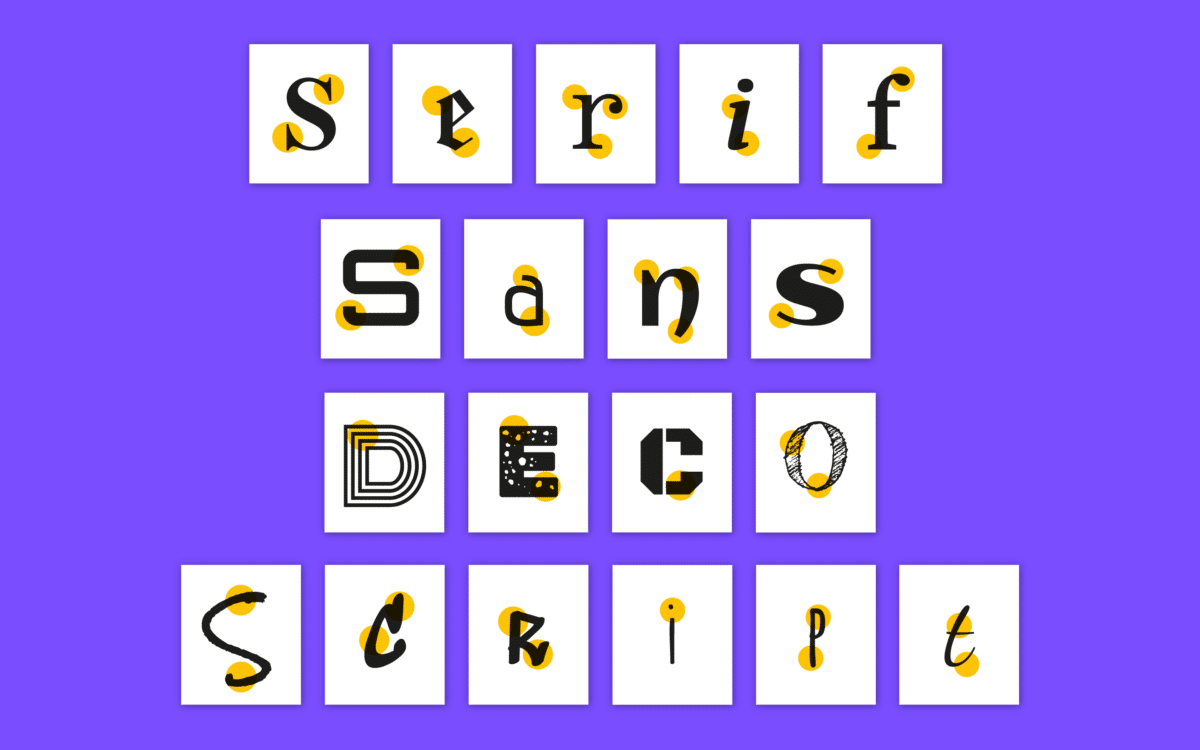
Polices de caractères et polices : qu'est-ce qu'une police de caractères ?
Une police de caractères est un ensemble spécifique de caractéristiques de conception choisies pour une série de caractères et de lettres. Par exemple, si vous regardez la police Arial, vous remarquerez une police simple sans empattement avec des courbes et des lignes soigneusement espacées.
Une police de caractères définit les éléments qui rendent un ensemble de caractères unique, des empattements spécifiques aux fioritures et à l'équilibre des lettres majuscules et minuscules.
Il existe de nombreux styles de caractères différents, tels que :
Serif
Les polices de caractères Serif sont définies par les "empattements" ou les pieds sur diverses lettres. Ce sont quelques-unes des polices de caractères les plus traditionnelles disponibles aujourd'hui, souvent associées à des concepts tels que l'héritage, l'histoire, la sophistication et la crédibilité.
Sans empattement
Une police de caractères sans empattement est une option plus moderne, amicale et conviviale destinée à rendre les entreprises et les marques plus détendues et informelles. Ces polices de caractères éliminent les pieds "empattement" des lettres et créent ainsi une image plus décontractée.
Les polices de caractères sans empattement sont souvent très faciles à lire et sont courantes dans le monde numérique.
Décoratif
Une police de caractères décorative utilise une multitude d'éléments différents, des empattements et fioritures accrocheurs aux éléments tourbillonnants pour capter l'attention de leur public.
Les polices décoratives sont généralement destinées à de plus petites quantités de texte que les alternatives sans empattement ou avec empattement, car leurs éléments compliqués peuvent les rendre un peu plus difficiles à lire.
Scénario
À ne pas confondre avec une police écrite en italique, une police de caractères de script est lorsque les lettres et les caractères sont conçus pour ressembler à une écriture manuscrite naturelle et cursive. Ces polices sont les plus courantes chez les marques qui souhaitent obtenir une touche unique, conviviale et artisanale pour leur esthétique.
Semblables à leurs homologues décoratifs, les polices de caractères script peuvent être difficiles à lire dans des tailles plus petites, ce qui signifie qu'elles sont plus couramment utilisées pour les en-têtes et les logos.
Polices et polices de caractères : qu'est-ce qu'une police ?
Donc, si une police de caractères est l'élément de conception nécessaire pour différencier les caractères de différents groupes, qu'est-ce qu'une police ? En termes simples, le terme «police» fait référence au poids, à la taille et au style de la police de caractères.
Les entreprises qui adoptent des stratégies de typographie pour leur image de marque ne choisissent pas entre une police ou une police de caractères, mais sélectionnent une police de caractères globale, puis choisissent une ou deux polices au sein de la famille.
Par exemple, vous pouvez choisir la police Times New Roman pour le contenu du corps du blog de votre site Web et choisir différentes options de police pour les en-têtes et les sous-titres.
Une police en gras et en italique dans Times New Roman attirerait l'attention sur une zone spécifique si le reste de la police sur la page était d'une taille et d'un poids plus petits.
Les polices ont des « familles » ou des groupes de polices associées. Par exemple, Arial est une police de caractères avec une gamme de caractéristiques de conception uniques pour les lettres et les caractères.
Cependant, la police de caractères Arial a un certain nombre de polices connectées. Vous pouvez créer un design complètement différent avec Arial en taille 16, souligné, gras et écrit en italique, à Arial en taille 11 sans modifications supplémentaires.
Les moyens les plus courants de modifier une police sont avec :
- Taille : ajustez la taille des points dans votre logiciel de conception.
- Gras : la mise en gras d'une police augmente son poids.
- Crénage : un espacement étroit ou étendu d'une police peut modifier son apparence.
- Italique : une police en italique penche d'un côté.
Pourquoi le débat entre police et police de caractères est-il important ?
Les polices de caractères et les polices sont des éléments de la « typographie » choisie par une entreprise. Le terme « typographie » fait référence à la manière dont le texte est disposé dans un design, par exemple pour votre logo, votre site Web, votre carte de visite et une foule d'autres éléments.
Grâce à la pratique de la typographie, les concepteurs manipulent le texte pour l'adapter de manière esthétique à un design, sans compromettre la lisibilité.
Les concepteurs ne créent pas de polices de caractères avec la typographie, mais travaillent avec des polices de caractères et des polices existantes pour créer une image spécifique pour leur public cible. Connaître la différence entre la police de caractères et la police ici est crucial.
Si votre entreprise travaille avec une équipe de conception et prétend ne vouloir utiliser qu'une seule police pour l'ensemble de votre contenu, vous ne lui donnez pas beaucoup de latitude pour faire ressortir les différents éléments de votre projet.
Cependant, vous pouvez dire à une équipe de branding que vous ne souhaitez travailler qu'avec une seule police de caractères, tout en obtenant un atout efficace.
En effet, les entreprises peuvent travailler avec différentes polices dans une police de caractères pour initier certains effets. Une police en gras peut attirer l'attention sur une information importante dans un article ou sur une page Web.
Une police en italique peut distinguer une certaine partie du contenu du reste, en identifiant une citation ou un titre de livre. Différentes tailles de police peuvent rendre les morceaux de texte plus ou moins accrocheurs sur une page.
Avez-vous besoin de connaître la différence entre la police et la police de caractères?
Si vous n'êtes qu'un Joe moyen intéressé à en savoir plus sur la typographie, la plupart des gens ne vous appelleront pas pour avoir mélangé la police et la police de caractères. Cependant, pour un designer ou un professionnel du branding, savoir différencier ces deux termes est crucial.
Bien que comprendre la différence entre les polices de caractères et les polices puisse sembler un peu pédant au début, c'est une partie importante de la compréhension des différents éléments responsables d'une image de marque efficace. Même les propriétaires d'entreprise pourraient bénéficier de connaître la différence entre ces termes.
Être capable de dire à votre designer que vous voulez un certain type de police de caractères communique le style que vous voulez, tout en lui donnant la possibilité de trouver la bonne police pour votre projet. Cependant, dire que vous voulez une certaine police rend votre vision spécifique aussi claire que possible.
Maintenant que vous connaissez la différence entre les polices de caractères et les polices, vous pouvez poursuivre votre parcours de marque en toute clarté.